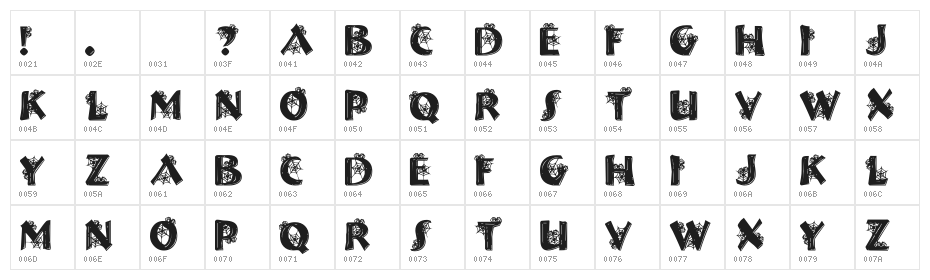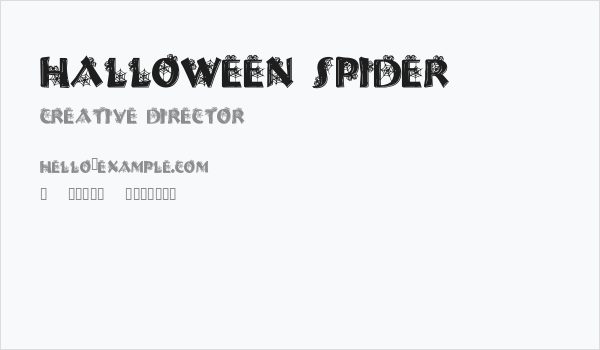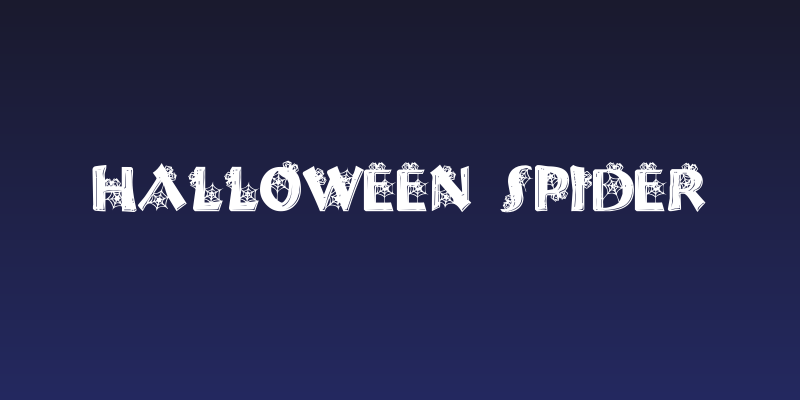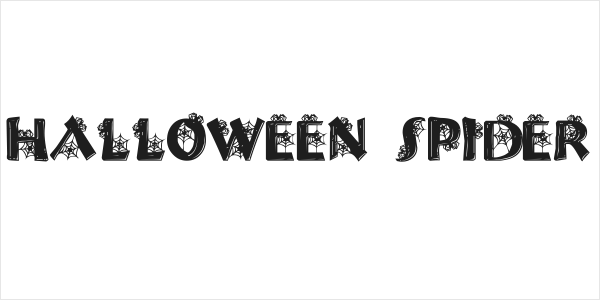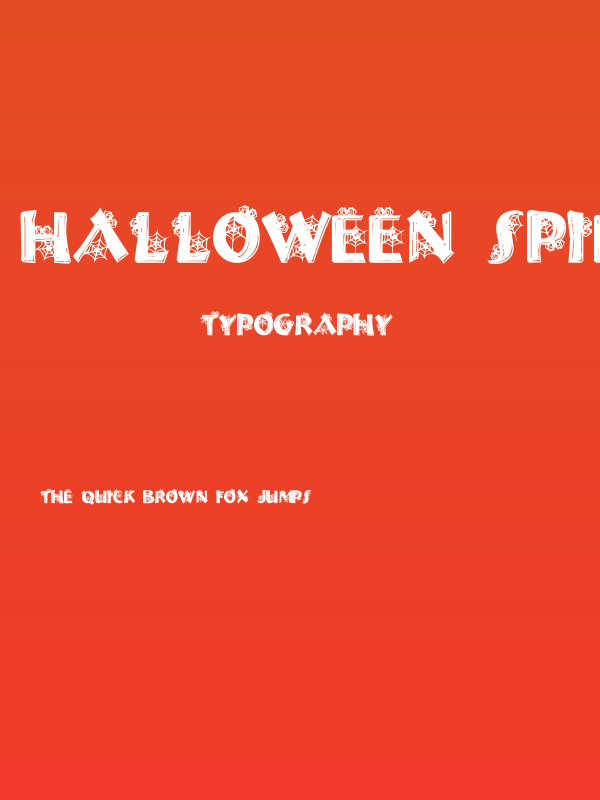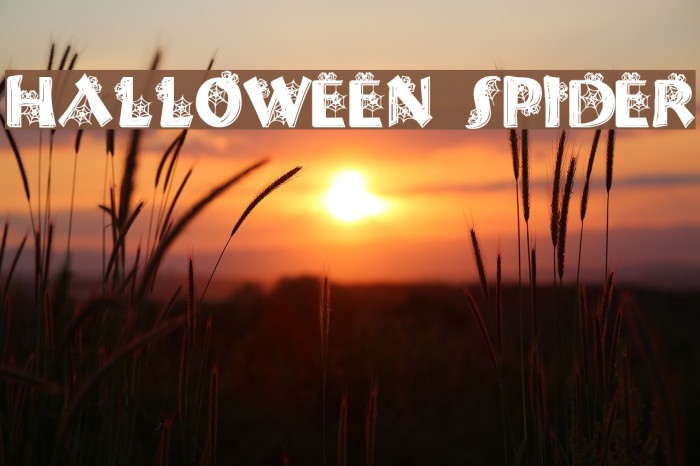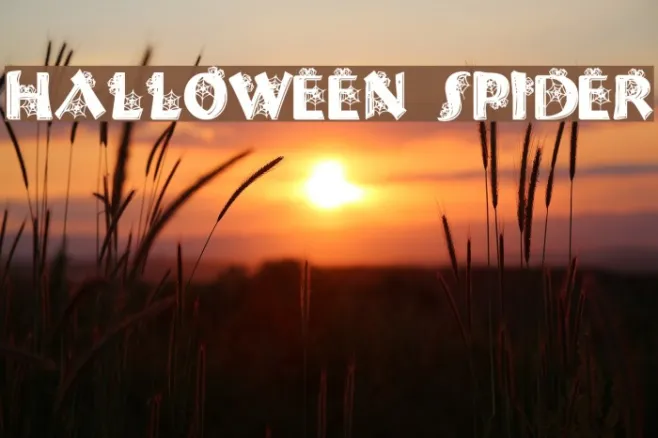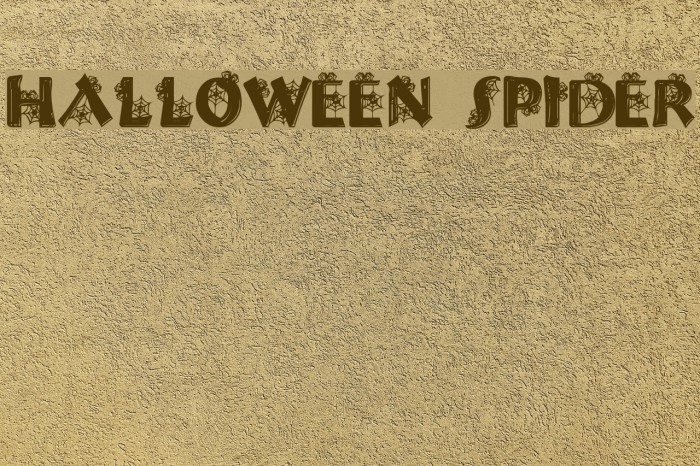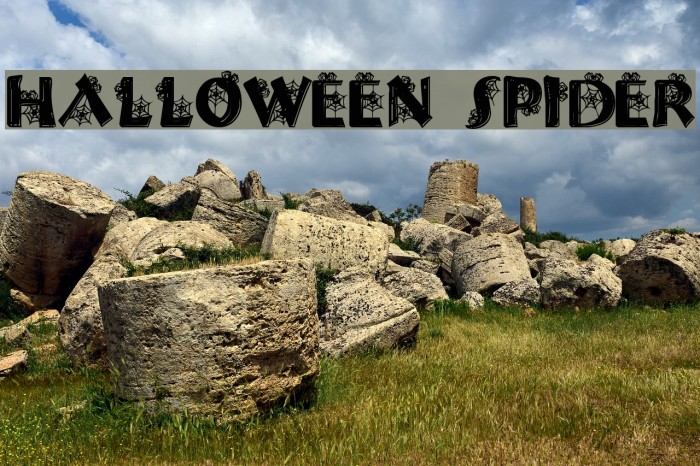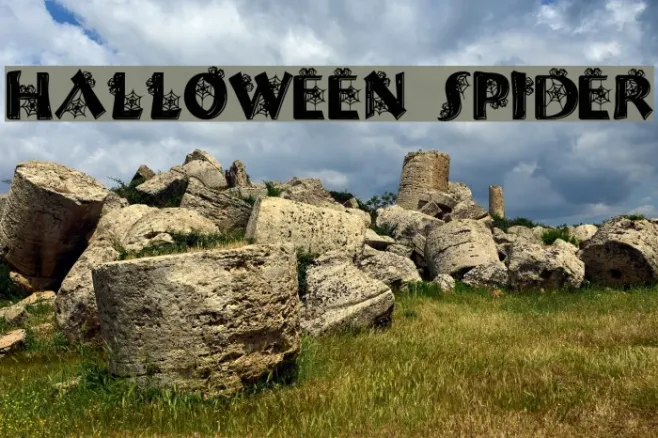
Halloween Spider Font
✎ Decorative
| Vorgeschlagene Projekte | Perfect for Halloween invitations, party decorations, themed posters, and event branding. |